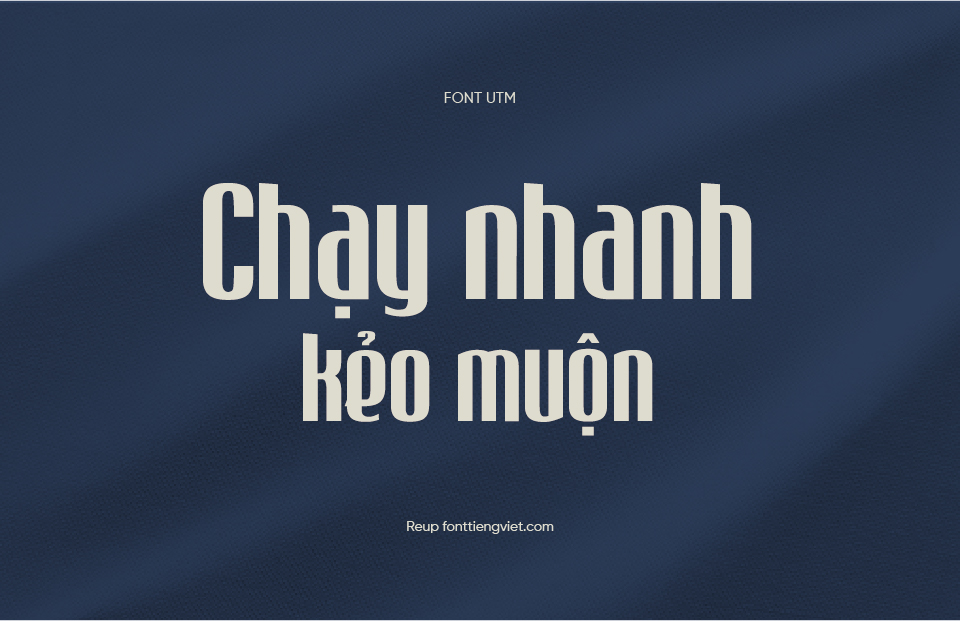
Tên font: Font Việt hóa VIP Kimotto Condensed Light – Phong Cách Hoài Cổ Với Thiết Kế Cao Hẹp Ấn Tượng
Tác giả: Laire Banyu Sandi Pawenang
Kimotto Condensed là một font chữ không chân (sans-serif) nổi bật với thiết kế hẹp và độ cao lớn, mang đậm dấu ấn hoài cổ. Với những đường nét đơn giản nhưng độc đáo, font này tái hiện lại cảm giác retro, vintage nhưng vẫn giữ được sự mạnh mẽ và hiện đại, rất thích hợp cho các thiết kế muốn gây ấn tượng mạnh bằng chữ.
Sans-serif, không chân, hiện đại nhưng vẫn giữ phong cách cổ điển